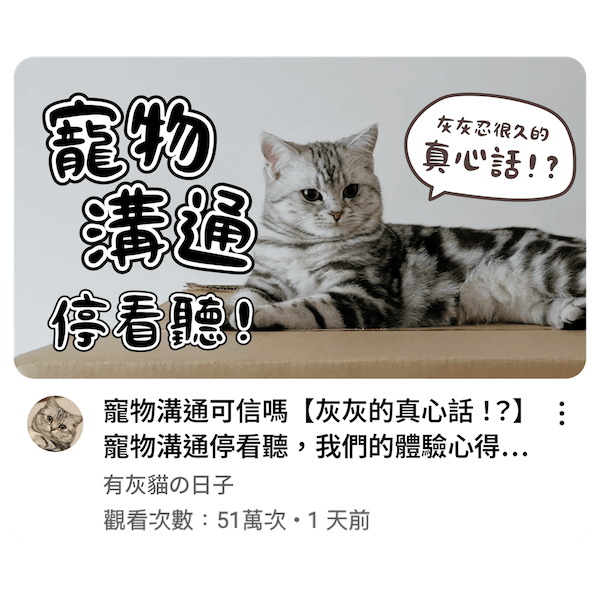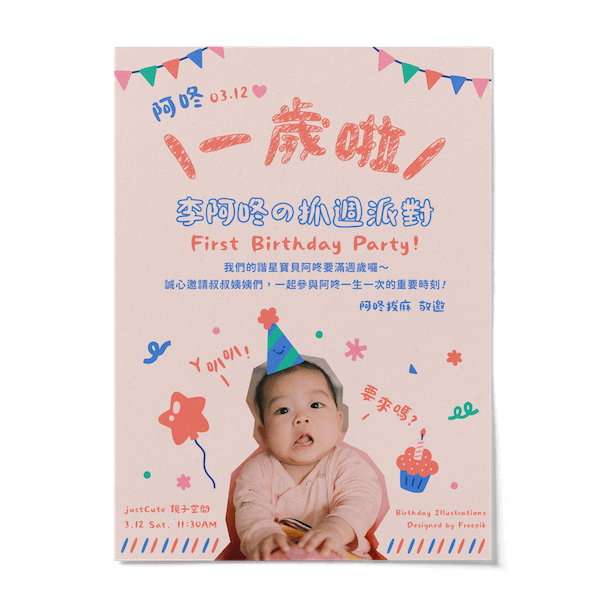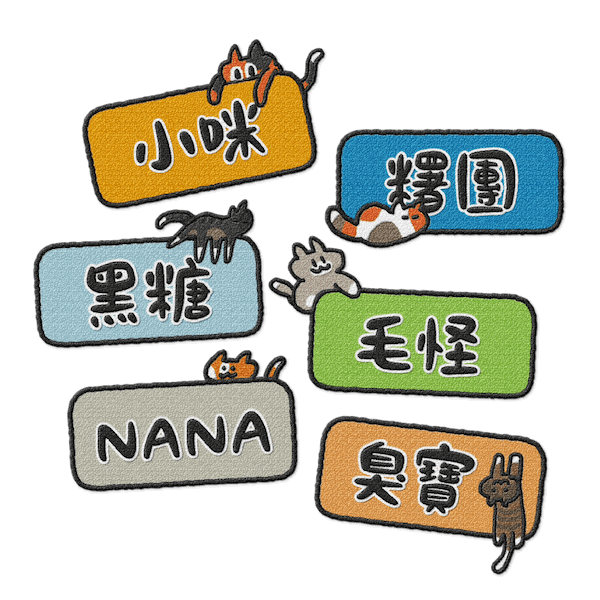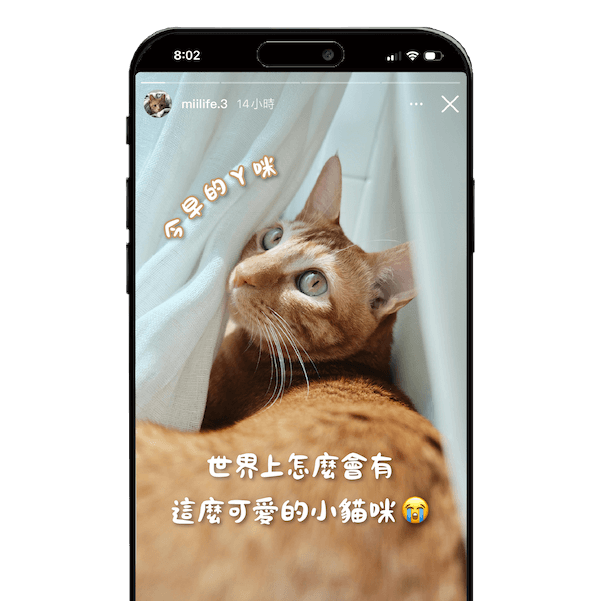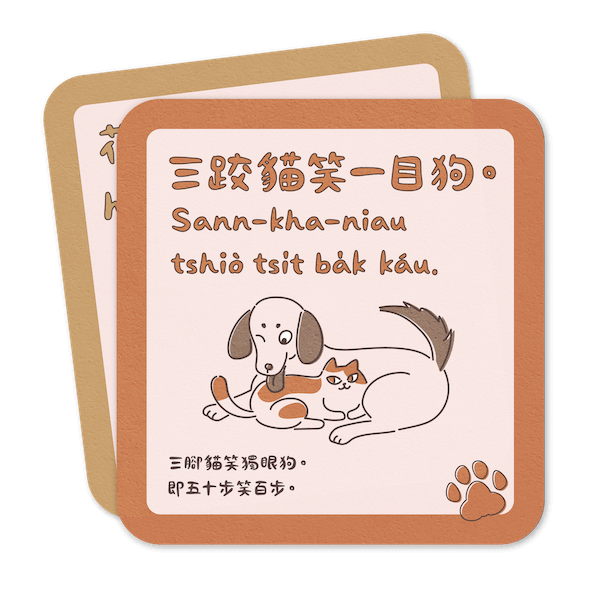
阿瑪手寫體
「阿瑪手寫體」是為了黃阿瑪頻道影片封面創作的手寫體,
貓尾筆畫靈活俏皮,自然手寫率性圓潤,就像橘貓。
用於特效綜藝字卡與社群圖文標題,更能發揮效果。
字型設計師
黃狸貓
在黃阿瑪的後宮生活擔任奴才之一。為了持續服侍罐罐,日以繼夜寫了超過九千字,成為宇宙第一由貓族創造的字體,使主子阿瑪龍心大悅。